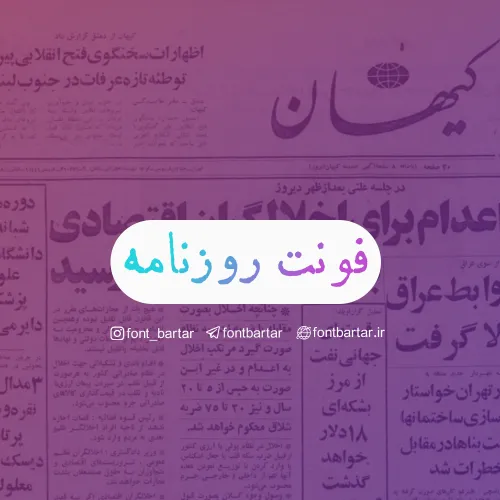
فونت فارسی روزنامه
فونت روزنامه
فونت فارسی روزنامه
فونت فارسی زیبا به نام روزنامه که توسط طراح خلاق ناصر ابراهیمی طراحی شده است. از این فونت زیبا و خلاقانه می توانید در تیتر های طرح های گرافیکی خود استفاده کنید. قابل توجه دوستان فونت فارسی روزنامه با یک پسوند ttf قرار داده شده است.
فونت روزنامه مورد استفاده برای: